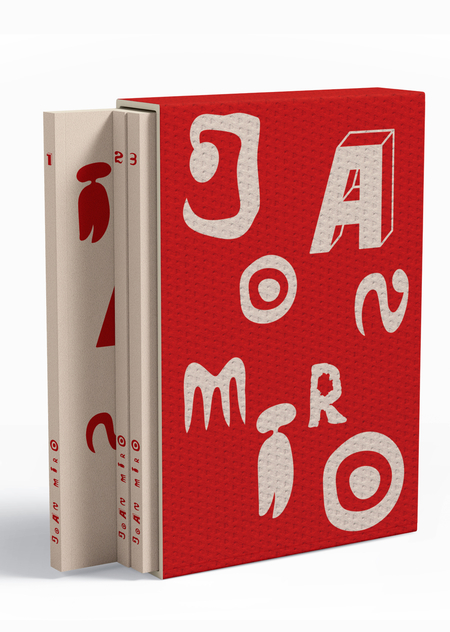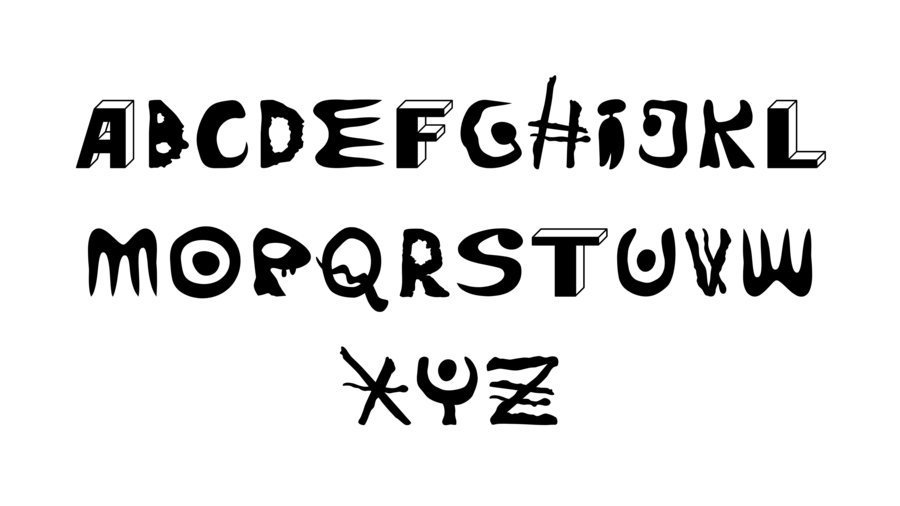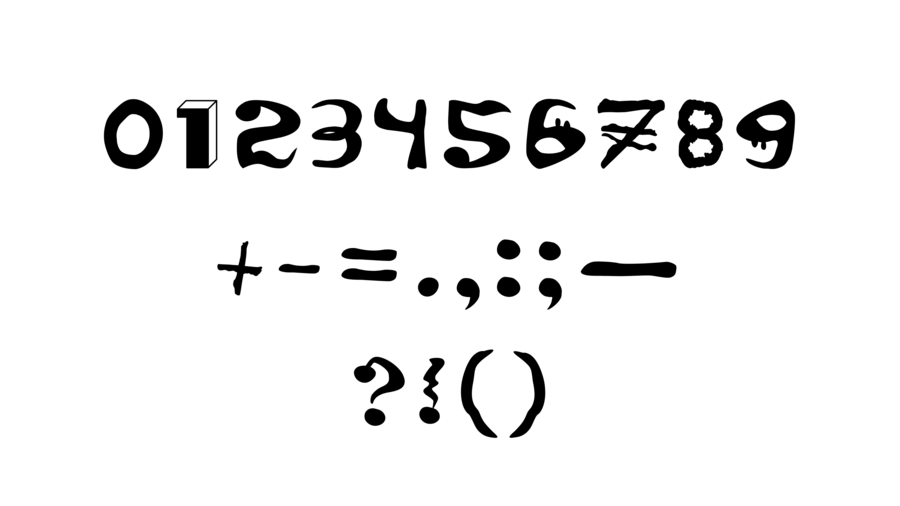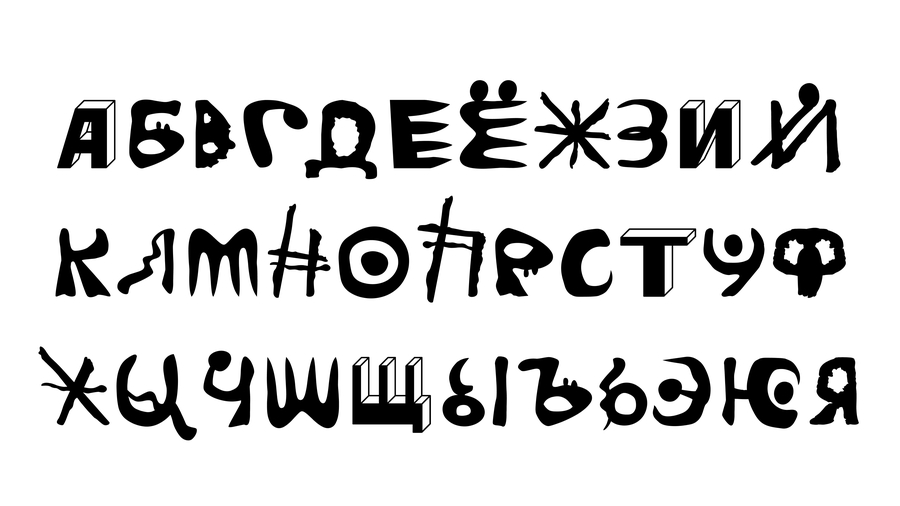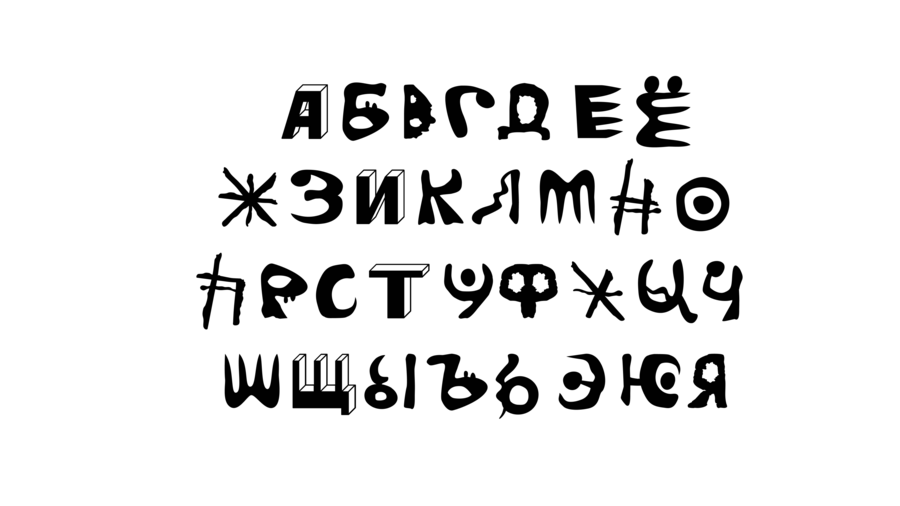
Хоан Миро — каталонский художник, скульптор и график. Он изобрёл свой визуальный язык, с устойчивыми мотивами (изображениями месяцев, звёзд, глаз, птиц, фигур-символов, лестниц) и характерной «живой» линией. Этот язык обладает собственной грамматикой и ритмикой. Элементы повторяются, варьируются, переходят из одной работы в другую.
При работе над шрифтом и айдентикой я переводила знаки и символы Миро в форму букв, строящихся из изонгутых линий, асимметричных «пятен» и каркасных конструкций.
Композиция шрифта и его размещение в макетах кажутся хаотичными, но при этом имеют свой ритм, отсылающий к полотнам Миро. Я старалась подчеркнуть в шрифте игривость, космическое ощущение пространства и свободу линий.